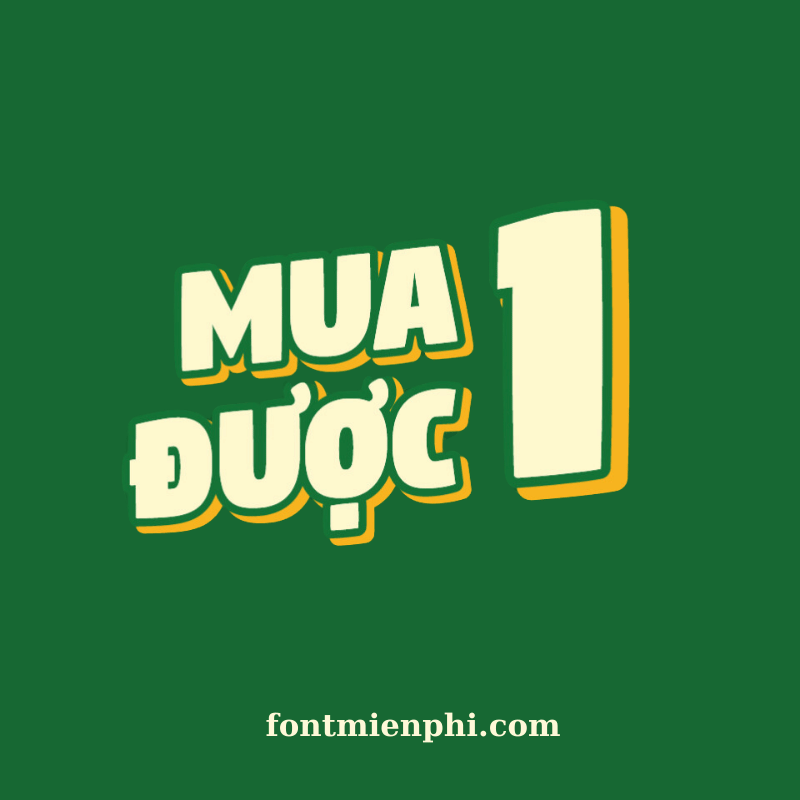
Font Việt Hóa 1FTV VIP Digital – Phong Cách Độc Đáo Cho Thiết Kế
Giới Thiệu
Font Việt hóa 1FTV VIP Digital là bộ font chữ cao cấp, được thiết kế tinh tế với khả năng hỗ trợ tiếng Việt đầy đủ. Với phong cách hiện đại, đa dạng kiểu chữ, font này phù hợp cho nhiều dự án sáng tạo như thiết kế đồ họa, quảng cáo, in ấn và digital marketing.
Đặc Điểm Nổi Bật
- Hỗ trợ tiếng Việt chuẩn: Đầy đủ dấu và ký tự đặc biệt, đảm bảo tính thẩm mỹ và dễ đọc.
- Đa dạng phong cách: Từ thanh lịch, sang trọng đến cá tính, phù hợp với nhiều ngành nghề.
- Tối ưu cho digital: Thiết kế sắc nét, hiển thị đẹp trên mọi nền tảng số.
Ứng Dụng Font Việt hóa 1FTV VIP Digitalt
1FTV VIP Digital là lựa chọn hoàn hảo cho:
- Thiết kế logo, banner quảng cáo.
- Tạo ấn phẩm truyền thông, tạp chí.
- Thiết kế website, app mobile.
Kết Luận Font Việt hóa 1FTV VIP Digitalt